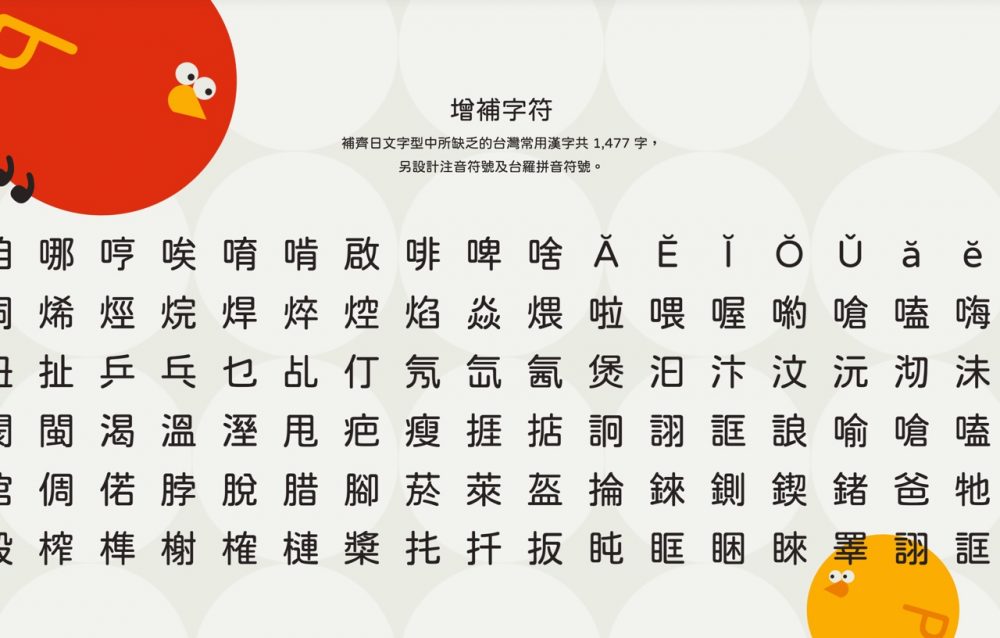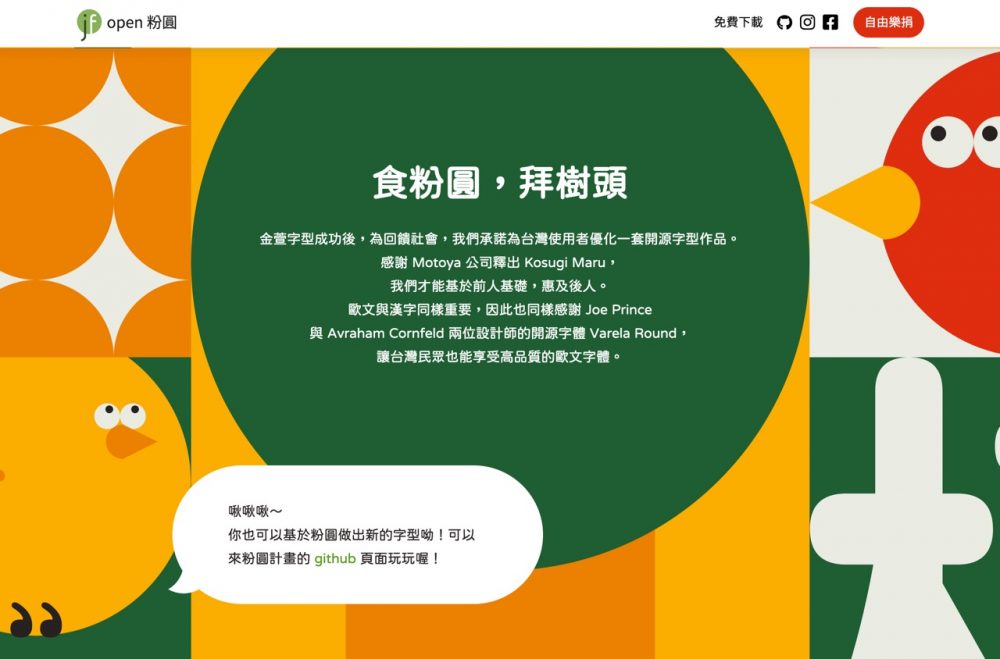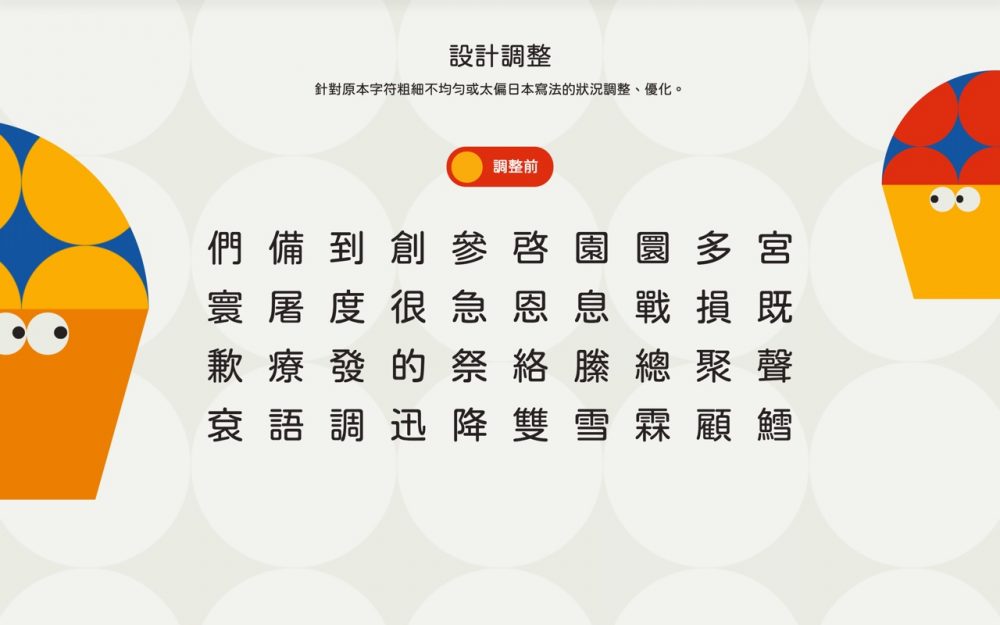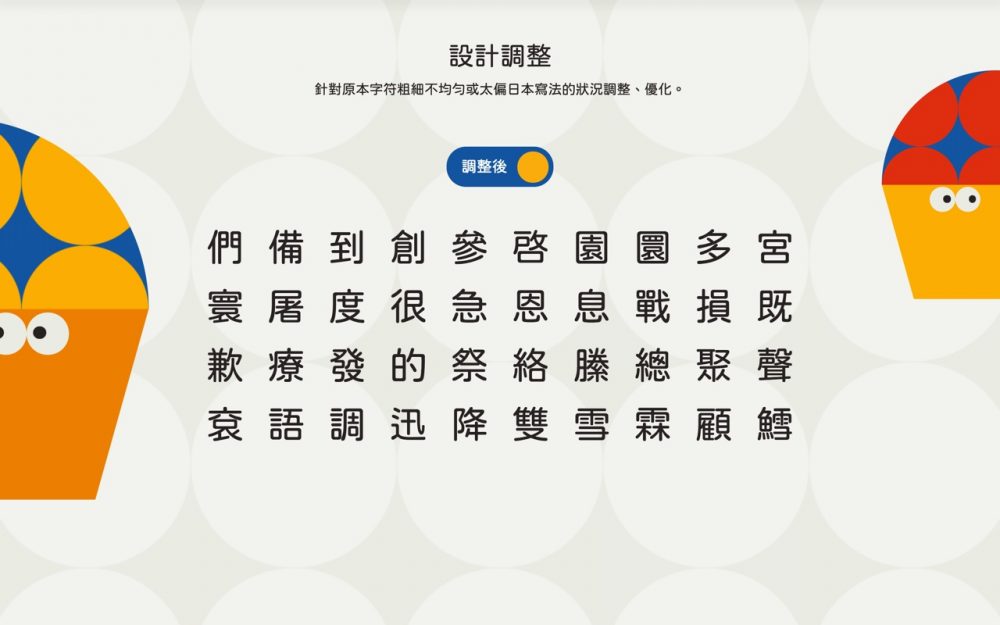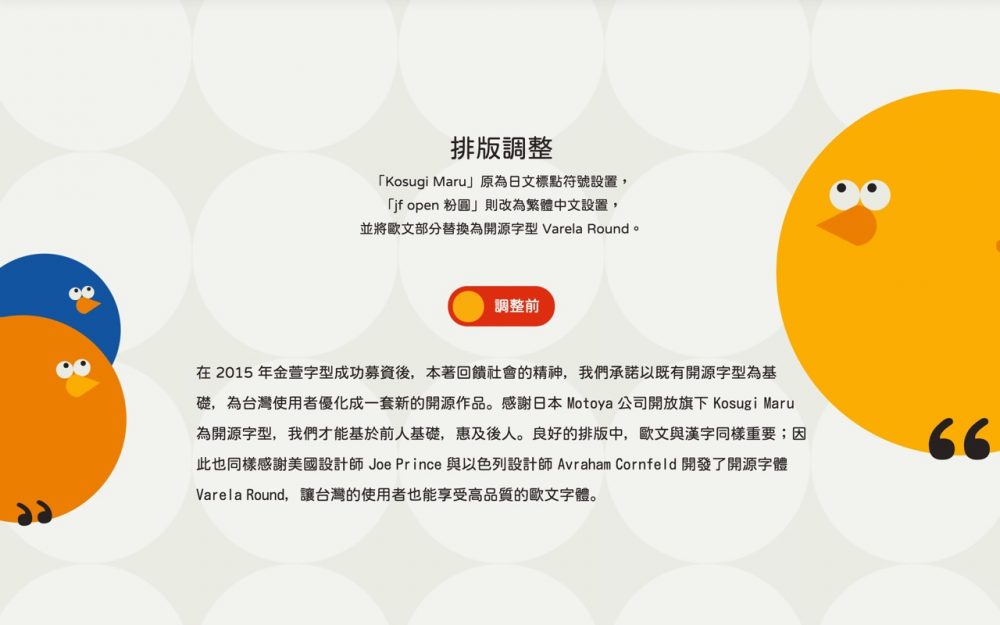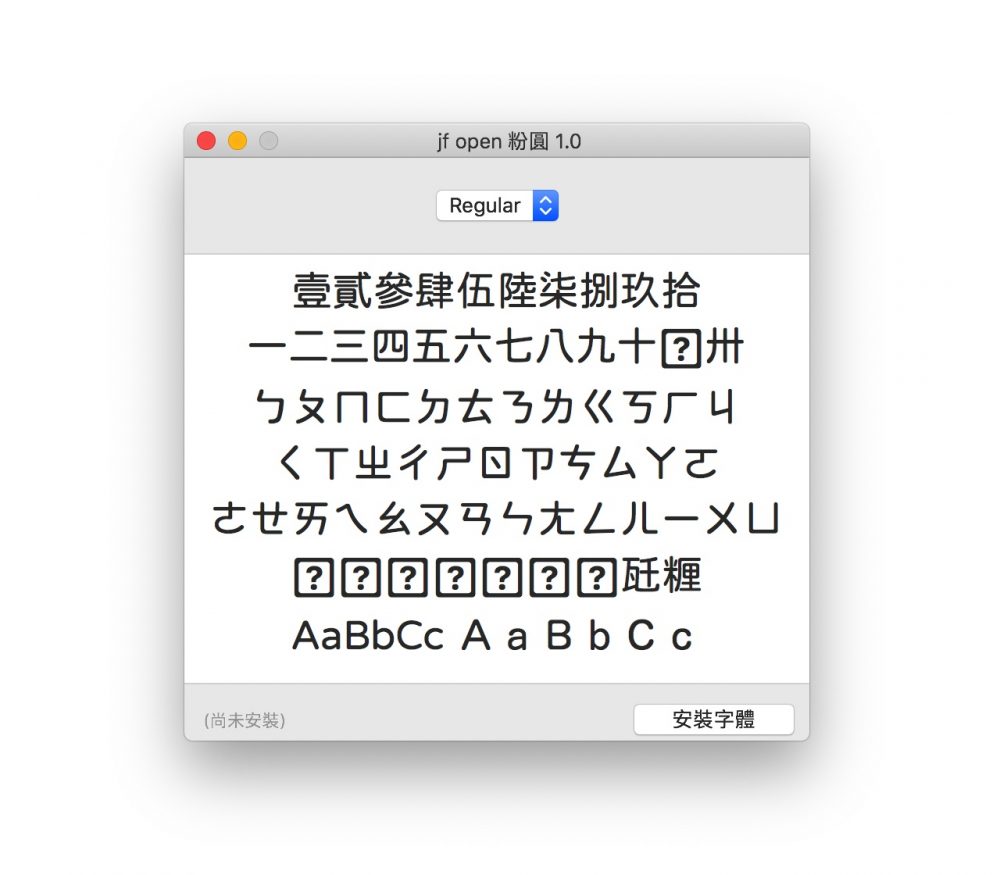
又一款免费可商用的中文字体!Open 粉圆字体火热下载中
jf open 粉圆字体在中英文和数字表现上都很理想,看起来有点胖胖的圆体搭配上可爱的官方网站设计令人爱不释手,刚好也补足思源黑体、思源宋体以外没有圆体的遗憾(虽然有使用者自行改造的思源柔黑体可用)。
jf open 粉圆字型是「就是字 justfont」新推出的免费中文字型,基于 Kosugi Maru(小杉圆体)改作,大家都知道如果找不到合适的中文字型,直接使用日文字型或许是个解决方案,但部分汉字在写法上和中文略有不同,标点符号位置也不一样,更大的问题是缺字,这会使得字型无法正确被使用在很多地方。
因此 justfont 找到一款日文的圆体字型加以改良,包括修正笔划的粗细(Kosugi Maru 最早是被使用在 Android 系统)、修正原字型粗细不均匀或转圆角时的小问题、比对繁体字找出需要修改的写法,同时补上一些常用字,加入注音及修正标点符号位置,让它更适合排版使用。
jf open 粉圆字体
- 基于 Kosugi Maru(小杉圆体)进行改作,英文部分采用 Varela Round;
- 补齐缺少的繁体中文字,调整标点符号位置及设计结构。
开启 jf open 粉圆字体官方网站,可以看到一系列的介绍和开发故事,简单来说,这个字型是以日文字体 Kosugi Maru 做为基础修改而来,补齐原字体缺少的常用汉字共 1,484 个,让这款字体可以被用户做为免费中文字体使用。
如果你想知道 jf open 粉圆字体做了哪些结构上的调整,网站也有调整前后的切换器,能快速比较一些文字修改前后的差异,例如原有字体粗细不均匀或太偏向日本写法的状况。
原有的日文标点符号位置和繁体中文不同,在 jf open 粉圆字体上也做了修改,欧文部分则替换为开源字型 Varela Round,在中文排版上看起来更美观舒适。
jf open 粉圆字体在中英文和数字表现上都很理想,看起来有点胖胖的圆体搭配上可爱的官方网站设计令人爱不释手,刚好也补足思源黑体、思源宋体以外没有圆体的遗憾(虽然有使用者自行改造的思源柔黑体可用)。
- 基于 Kosugi Maru(小杉圆体)进行改作,英文部分采用 Varela Round;
- 补齐缺少的繁体中文字,调整标点符号位置及设计结构。